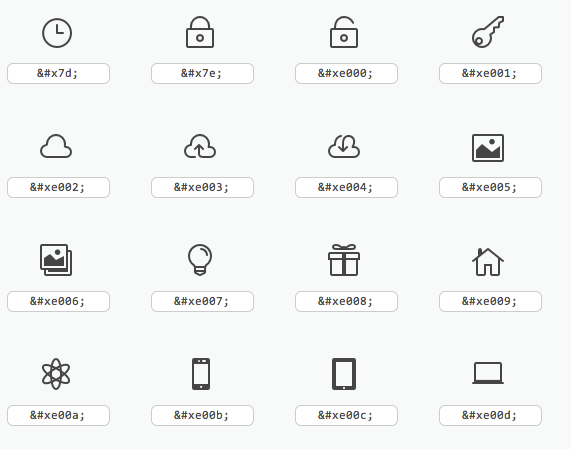
The Elegant Icon Fontはその名の通り、美しくてエレガントなアイコンフォントのセットです。
シンプルで曲線が綺麗なデザインのため、モダンなWebデザインに良く合います。
アイコンの種類も360と豊富で、よく使いそうなものが揃っています。
The Elegant Icon Fontはその名の通り、美しくてエレガントなアイコンフォントのセットです。
シンプルで曲線が綺麗なデザインのため、モダンなWebデザインに良く合います。
アイコンの種類も360と豊富で、よく使いそうなものが揃っています。